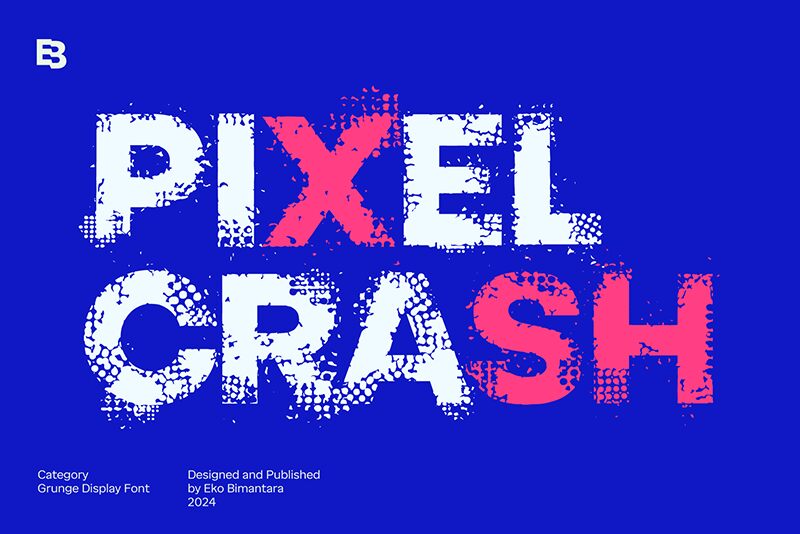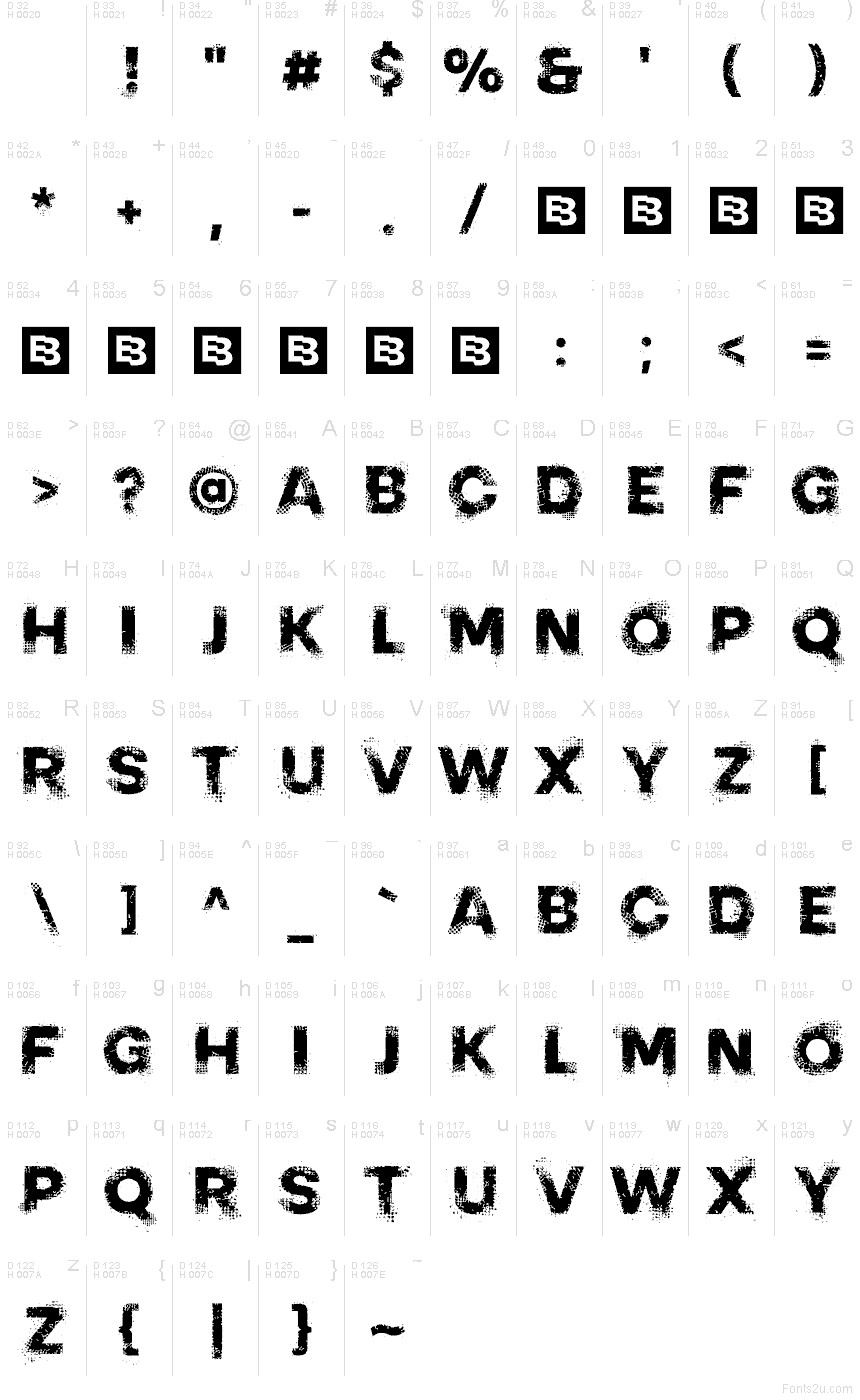
PIXEL CRASH TRIAL
Pixel Crash od Eko Bimantara je bezplatné, skreslené displejové písmo s blokovým pixelovým dojmom a drsnými, zlomenými okrajmi. Písmená vyzerajú ako ošúchané a fľakaté; vďaka roztrúseným medzerám a opotrebovanej textúre dodáva celému dizajnu vzhľad poškodeného arkádového automatu.
Pixel Crash funguje výborne na herných plagátoch, retro grafike, hudobných vizuáloch, letákoch na podujatia a výrazných akcentoch v logách. Fragmentované pixelové tvary sú mimoriadne užitočné, keď dizajn vyžaduje drsný digitálny glitch efekt bez toho, aby stratil svoju pevnú blokovú štruktúru.